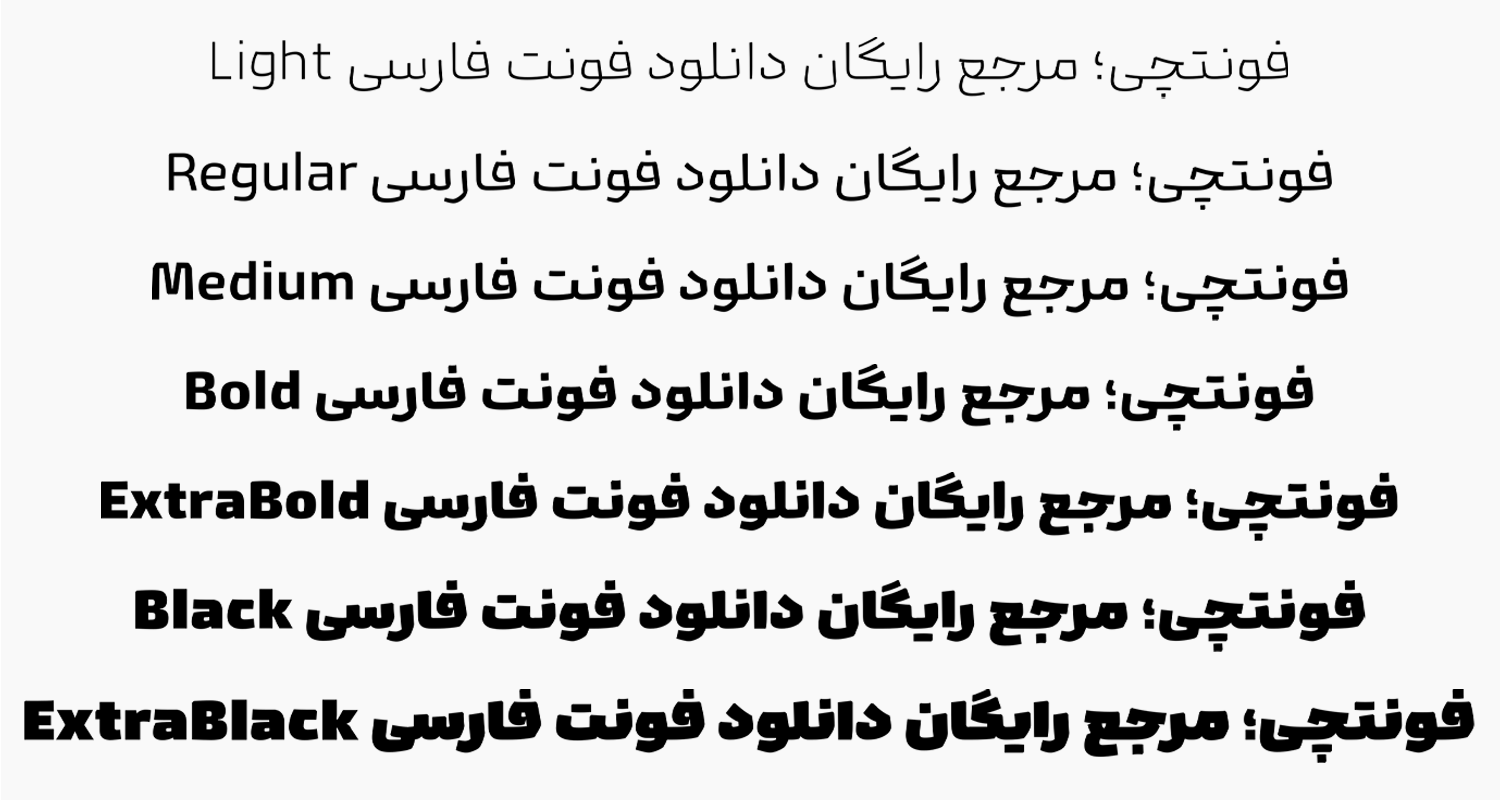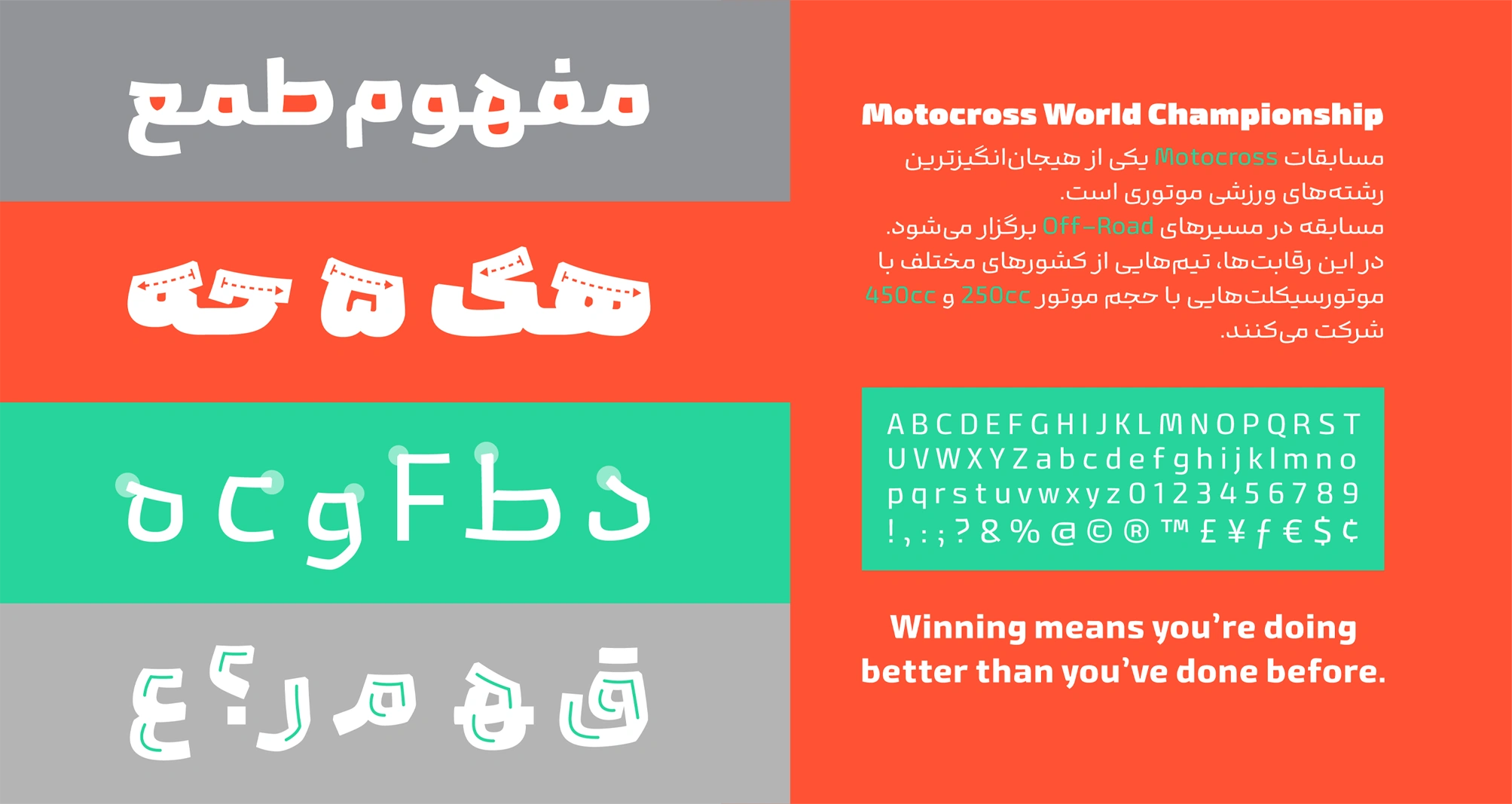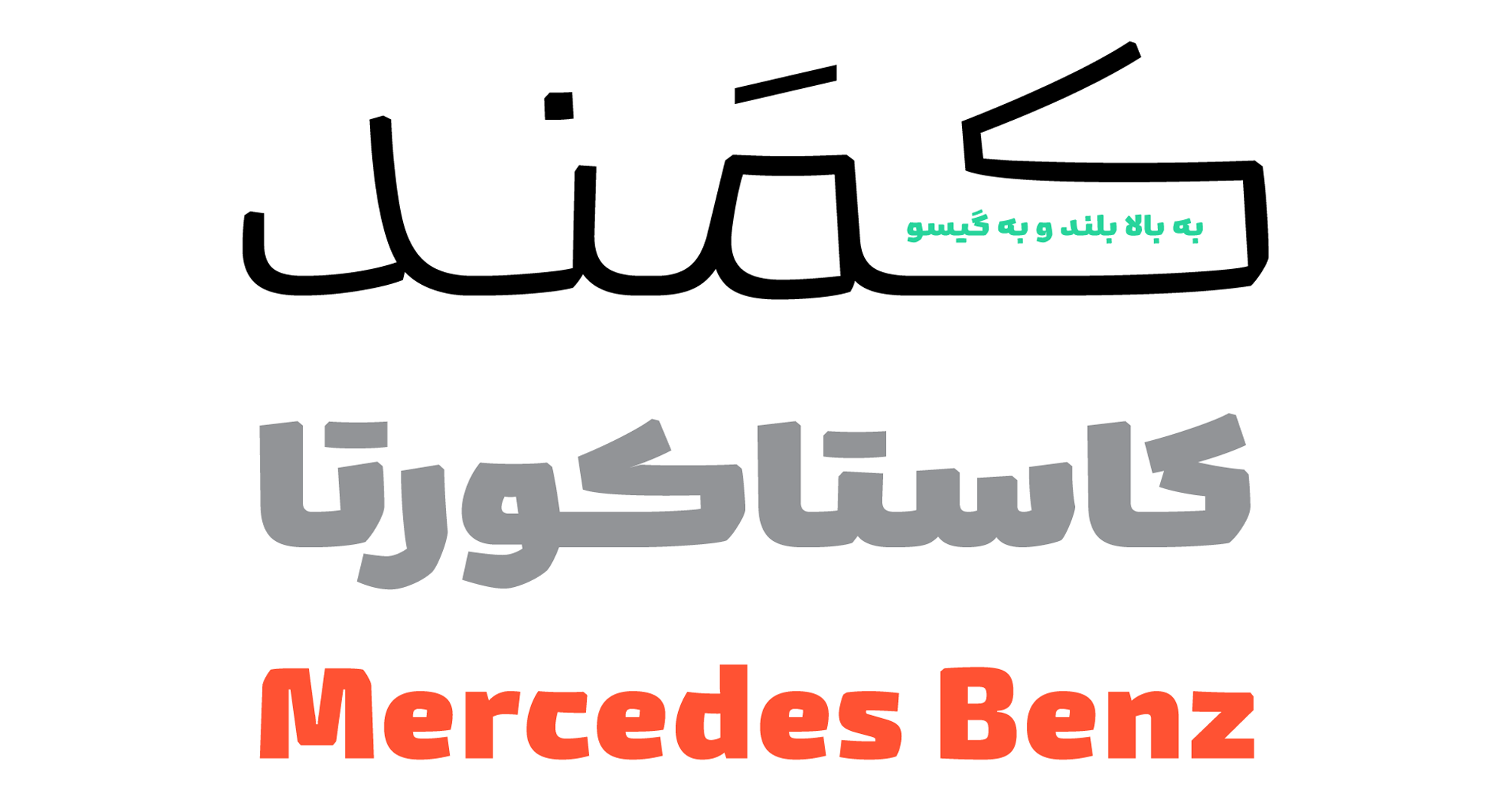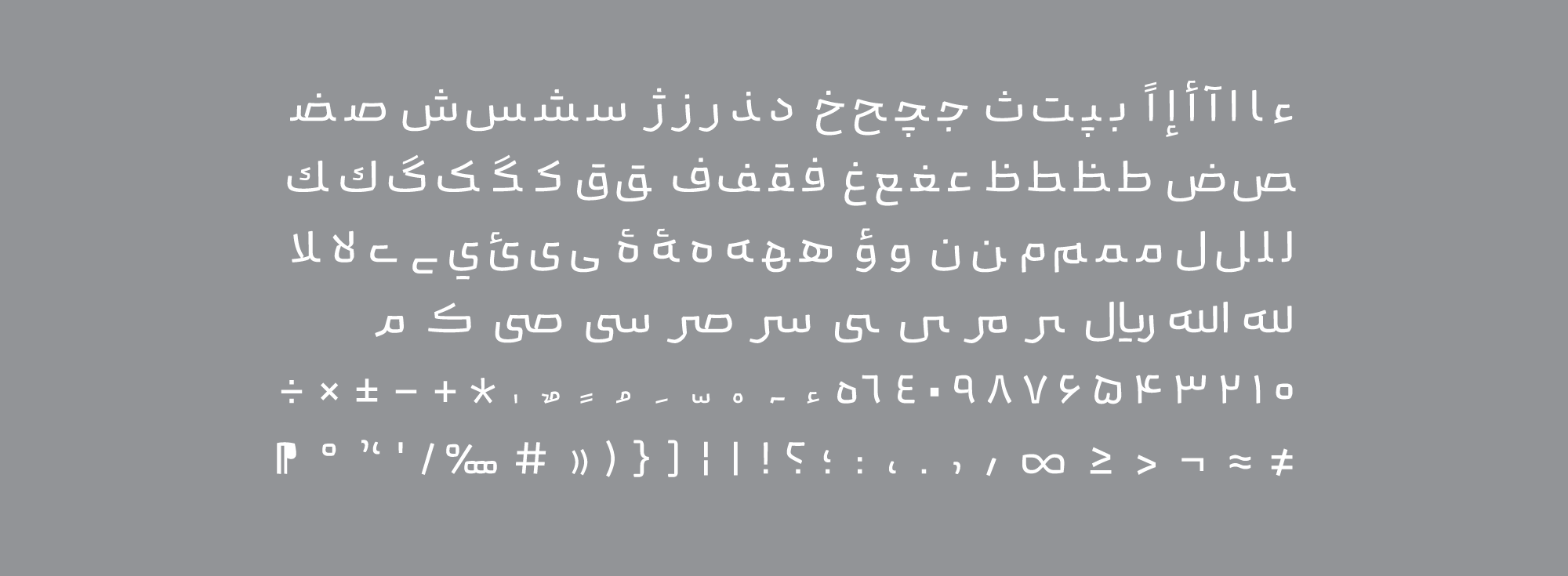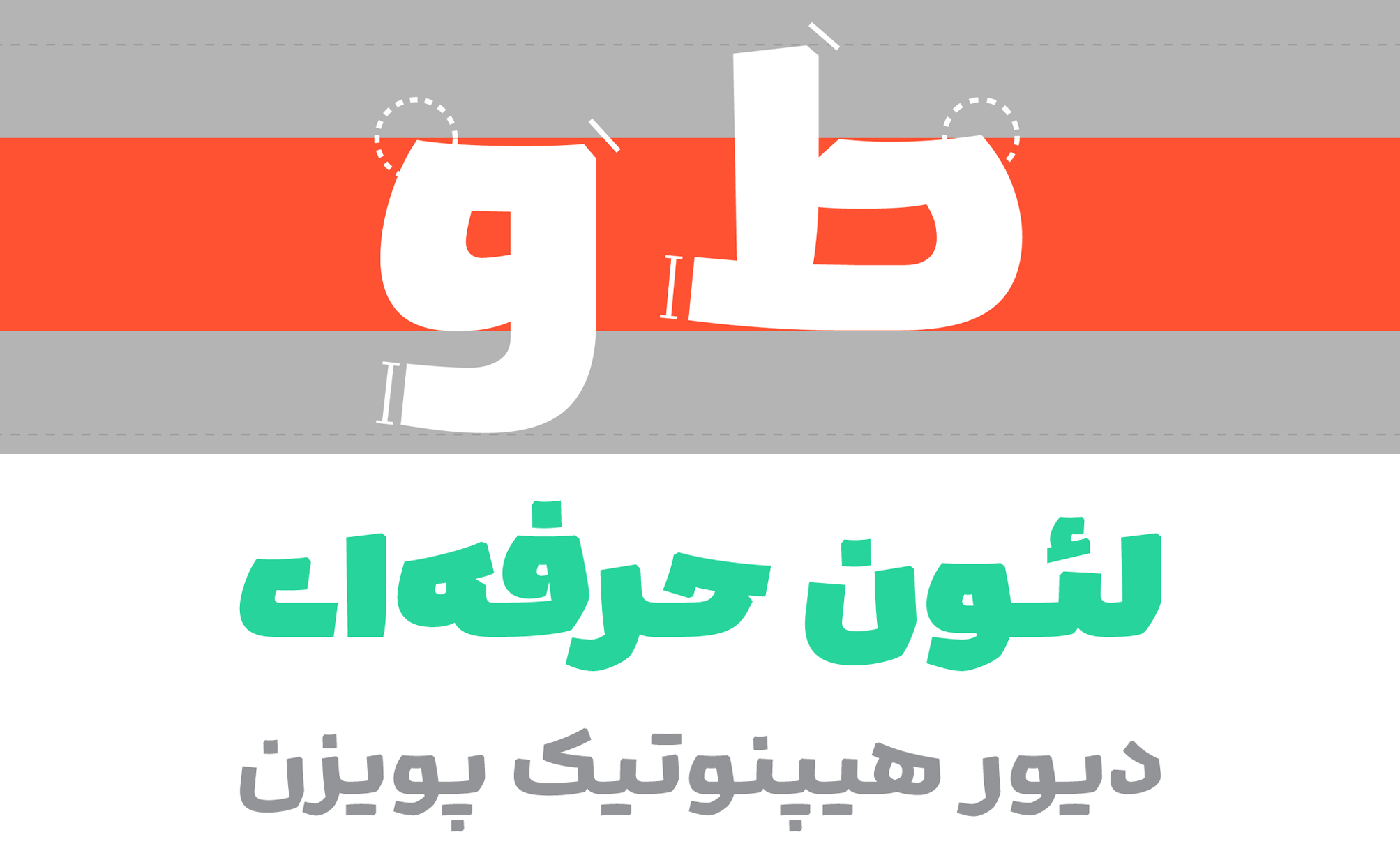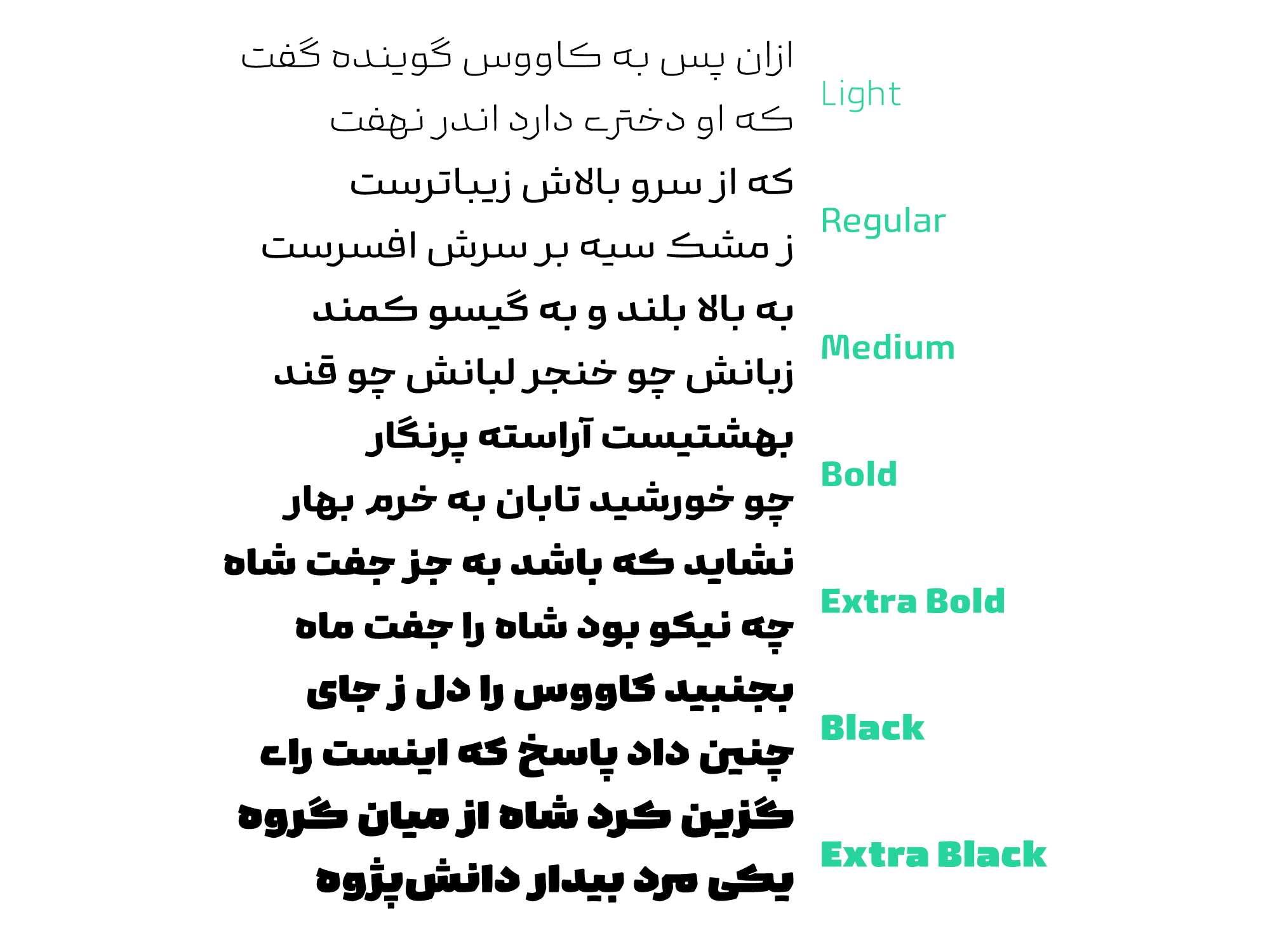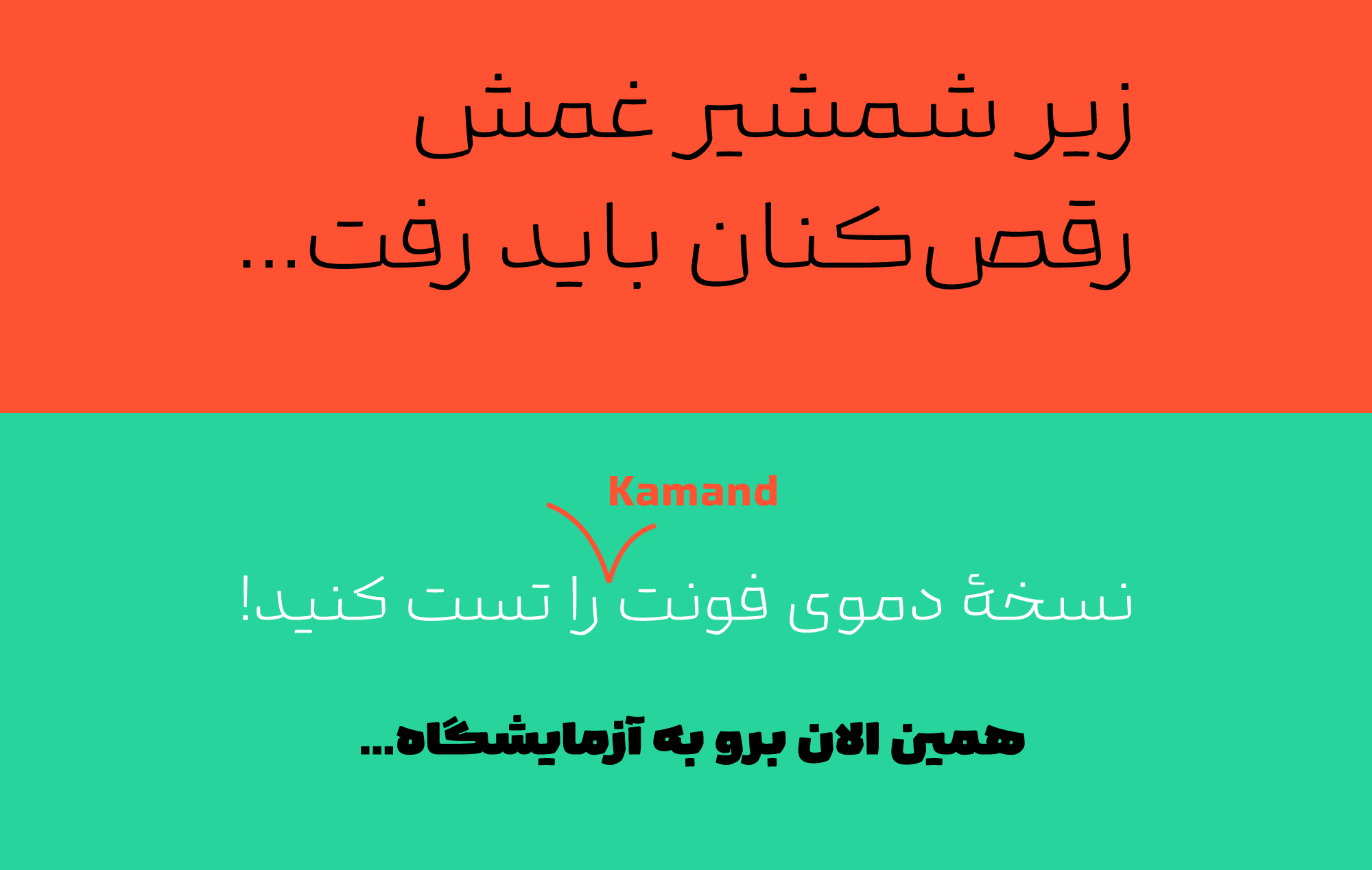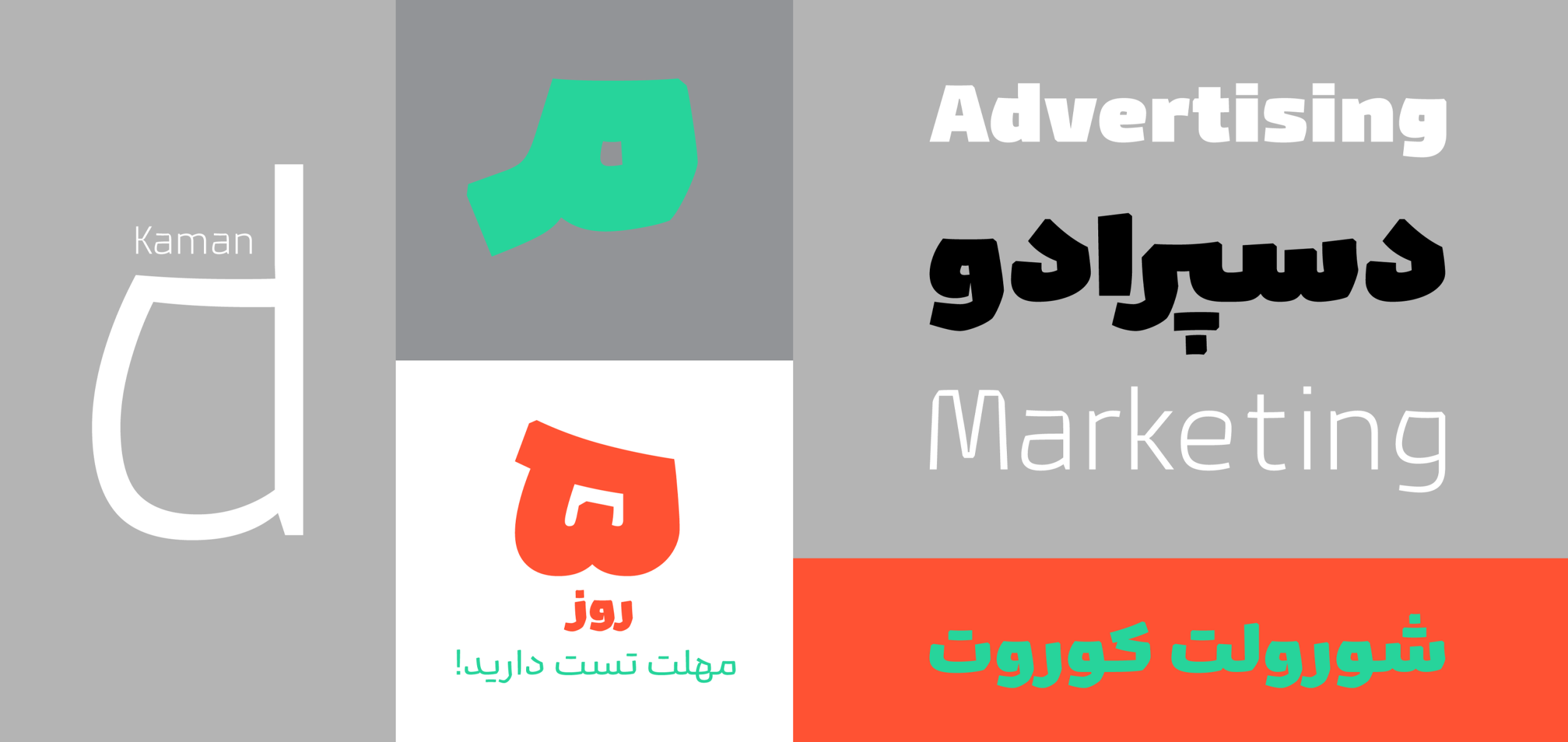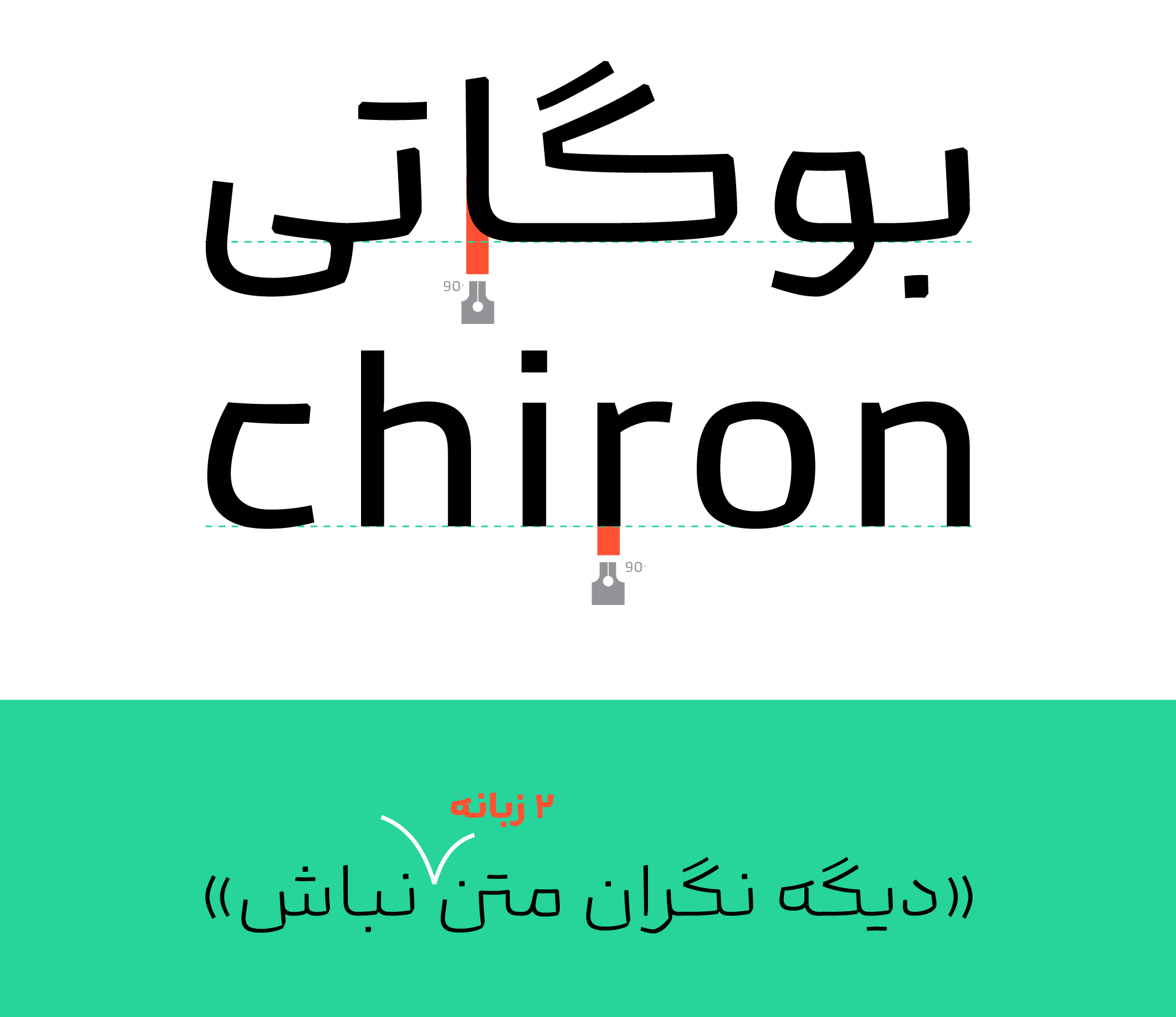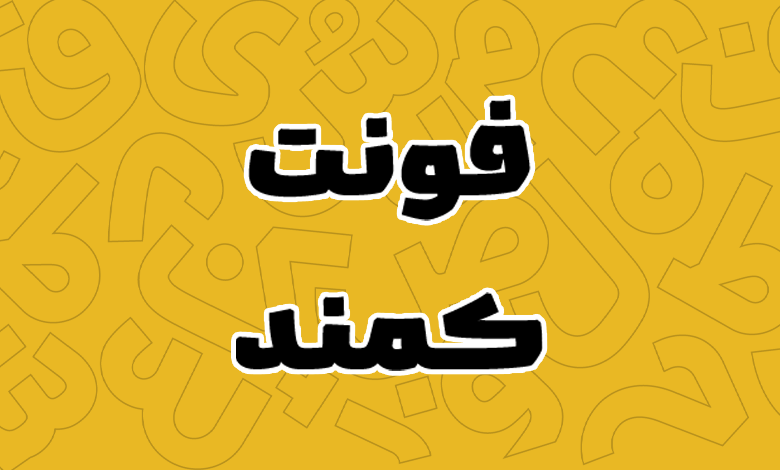
فونت کمند (Kamand)
فونت کمند (به انگلیسی: Kamand) در میان انبوهی از فونتهای خستهکننده و کلیشهای که در تبلیغات شهری و بیلبوردها بهکار رفته، لحنی متمایز دارد. فونت Kamand بهگونهای طراحی شده که در عین داشتن لحن آشنا، جذابیتی متفاوت و متمایز به نوشتهها میبخشد. فونت کمند رایگان نیست و در قالب ۳ بسته مختلف قابل خرید است.
این فونت میتواند به برندها کمک کند تا صدای خاص خود را به نمایش بگذارند و در میان شلوغیها به چشم بیایند. امید امامیان این قلم را در بهار و تابستان ۱۴۰۳ طراحی نموده و توسعه آن توسط مهدی ارشادی انجام گرفته است.
در ادامه به نقد و بررسی فونت کمند خواهیم پرداخت. اگر بهدنبال فونتی هستید که ظاهری بولد، نمایشی و ساختاری سرکش داشته باشد که در متون کوتاه و بلند گرفته تا فضای تبلیغاتی از آن استفاده کنید، در ادامه با ما همراه باشید.
فونت کمند به دلیل ویژگیهای منحصربهفردش، از جمله خوانایی بالا، طراحی مدرن و پشتیبانی از وریبل فونت، یک گزینه بسیار مناسب برای انواع پروژههای طراحی به شمار میآید. این فونت میتواند نیازهای طراحان حرفهای را بهخوبی برآورده کند و در پروژههایی مانند برندینگ، تبلیغات، و طراحی مجلات به کار گرفته شود.
- فونت وریبل کمند با پشتیبانی ۷ وزن:
فونت فارسی کمند شامل ۷ وزن مختلف (از Light تا Extra Black) ارائه شده است. این تنوع وزنی باعث میشود بتوانید از این فونت در پروژههای مختلف از جمله طراحیهای گرافیکی، جلد کتاب و حتی تبلیغات استفاده کنید.
بهعنوان مثال، وزن Light برای متنهای ساده و رسمی مناسب است، درحالیکه وزن Black و Extra Black تاثیرگذاری ویژهای در عناوین برجسته دارند.
پشتیبانی از وریبل فونت یکی از نقاط قوت کمند است. این قابلیت به شما اجازه میدهد وزنها و ضخامتهای مختلف را بهجای نصب تمامی ۷ وزن مختلف، فقط با نصب یک وزن متغیر یکجا داشته باشید. این موضوع همچنین امکان انعطاف بیشتری در طراحی با استفاده از نرمافزارهایی مثل فتوشاپ که از وزن متغیر پشتیبانی میکند فراهم میآورد.
در فونت Kamand از ترکیبات جایگزین متنوعی نیز بهمنظور ایجاد طراحیهای خاص و خلاقانه استفاده شده است. مطابق با تصاویر زیر بهسادگی میتوانید برخی حروف تکی یا ترکیبات دوتایی را با چند ظاهر مختلف تایپ کنید. با دانلود فونت کمند برای فتوشاپ دیگر نیاز نیز ساعتها زمان صرف برنامه الوستریتور برای تغییرات اینچنین در ترکیبات حروف کنید.
- ساختار کلی و سبک طراحی فونت کمند:
فونت کمند دارای طراحی مدرن و مینیمال است که ویژگیهای خاصی مانند زوایای ملایم، منحنیهای دقیق و دندانههای متعادل دارد. چشمیها و خط کرسی نیز بهخوبی با دیگر عناصر هماهنگ شدهاند و خوانایی بالایی را تضمین میکنند.
ترکیب این ویژگیها باعث شده فونت کمند در متون بلند همانقدر جذاب به نظر برسد که در متون کوتاه و عنوانها میتوان از آن انتظار داشت.
زوایای ملایم و منحنیهای متناسب باعث شدهاند که فونت کمند از خوانایی بالایی برخوردار باشد. این ویژگی در متون بلند بهویژه در روزنامهها و مجلات بسیار اهمیت دارد.
با این حال، در استفاده از وزنهای سنگینتر در متون کوچک، ممکن است کمی کاهش خوانایی مشاهده شود. اما در مقابل برای فضای تبلیغاتی، بهویژه بیلبوردهای سطح شهر، ظاهری بسیار نمایشی دارد.
- پشتیبانی از ۵ زبان متنوع:
فونت کمند از پنج زبان فارسی، عربی، کوردی، اردو و انگلیسی پشتیبانی میکند. طراحی دقیق حروف لاتین و هماهنگی آنها با حروف فارسی و عربی نشاندهنده توجه طراحان به یکپارچگی زبانهاست.
هماهنگی فوقالعاده بین حروف فارسی، عربی و لاتین نشان از طراحی دقیق و حرفهای این فونت دارد. این ویژگی برای پروژههایی که به چند زبان نیاز دارند، ایدهآل است. دقت بالا در طراحی دندانهها و هماهنگی چشمیها برای زبانهای خاورمیانهای باعث شده کمند جلوهای حرفهای و جذاب داشته باشد. این امر آن را به گزینهای مناسب برای برندینگ و تبلیغات تبدیل میکند.
فونت Kamand انگلیسی دارای طراحی اختصاصی است. این ویژگی امکان استفاده روان و هماهنگ از متنهای دوزبانه را فراهم میکند. در نتیجه، متون فارسی و انگلیسی بدون شکاف بصری کنار هم قرار میگیرند و یکپارچگی متن حفظ میشود. این قابلیت برای برندهایی که به طور همزمان در بازارهای داخلی و بینالمللی فعالیت میکنند، بینظیر است.
اگر در پروژههای خاص خود نیاز به ترکیب این قلم با فونتهای دیگر احساس شود، فونت مربع یا فونت انجمن میتواند یکی از انتخابهای نزدیک به این قلم باشد که تا حدودی سبک یکسانی دارند.
فونت کمند مناسب برای تبلیغات
کمند، تلفیقی از اصالت و جسارت است. اگرچه رفتار فرمی آن بر پایه خط نسخ بنا شده، اما جزئیاتی غیرمنتظره در طراحی آن دیده میشود که هیجان و پویایی خاصی به متن میبخشد. برشها و شکستهای غیرمنتظره در هر کاراکتر به متن جانی تازه میدهد و توجه مخاطب را به خود جلب میکند.
ارتفاع کوتاه صعود و نزولها (Ascender و Descender) به همراه فرمهای جمعوجور حروف، کمند را به گزینهای ایدهآل برای تبلیغات محیطی و فضای مجازی، خصوصا در نرمافزارهای کپ کات و اینشات تبدیل کرده است. این ویژگی به متن اجازه میدهد حتی در اندازههای کوچک نیز جذابیت خود را حفظ کند و در طراحیهای مدرن بدرخشد.
فونت کمند در طراحی خود حالتی شبیه به اسب سرکشی دارد که با وقار و آزادانه در دشتهای سبز حرکت میکند. این استعاره نهتنها زیبایی ظاهری فونت را به تصویر میکشد، بلکه حس پویایی و انرژی آن را نیز منتقل میکند. فرمهای بدیع و پرانرژی هر کاراکتر، به نوشتهها حالتی زنده و سرشار از حرکت میبخشد.
فونت کمند با صدای متمایز، امکانات گسترده و طراحی خلاقانه، انتخابی ایدهآل برای برندهایی است که به دنبال دیده شدن در میان رقبا هستند. از تبلیغات محیطی گرفته تا متون دوزبانه، این فونت میتواند هویت بصری منحصربهفردی به پروژهها ببخشد و متنها را به تجربهای جذاب و فراموشنشدنی تبدیل کند.